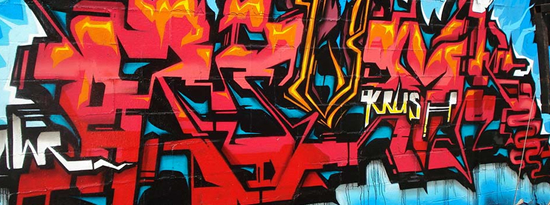
75 tipografías gratuitas con estilo graffiti
En todo momento los diseñadores gráficos tienen constante necesidad de buenos tipos de letras para sus creaciones, por ejemplo en el caso de que precisen de una tipografía con estilo graffiti, el primer paso es crearlas uno mismo a mano, en nuestro programa de diseño gráfico favorito, pero siempre pueden utilizar tipos de letras ya creados para utilizarlas en sus obras de arte.
Un artículo que me ha llamado la atención es 75 Free GRAFFITI FONTS, de Web design blog,nos proporcionan un buen surtido, con un total de 75 tipografías gratuitas con un estilo similar al que se emplea en el texto de los graffiti. Estos tipos de letras no solo los podemos emplear en nuestras creaciones, sino que también los podemos utilizar para inspiración en nuestros bocetos de obras de arte para luego plasmarlos en las paredes con los botes de aerosol o spray.